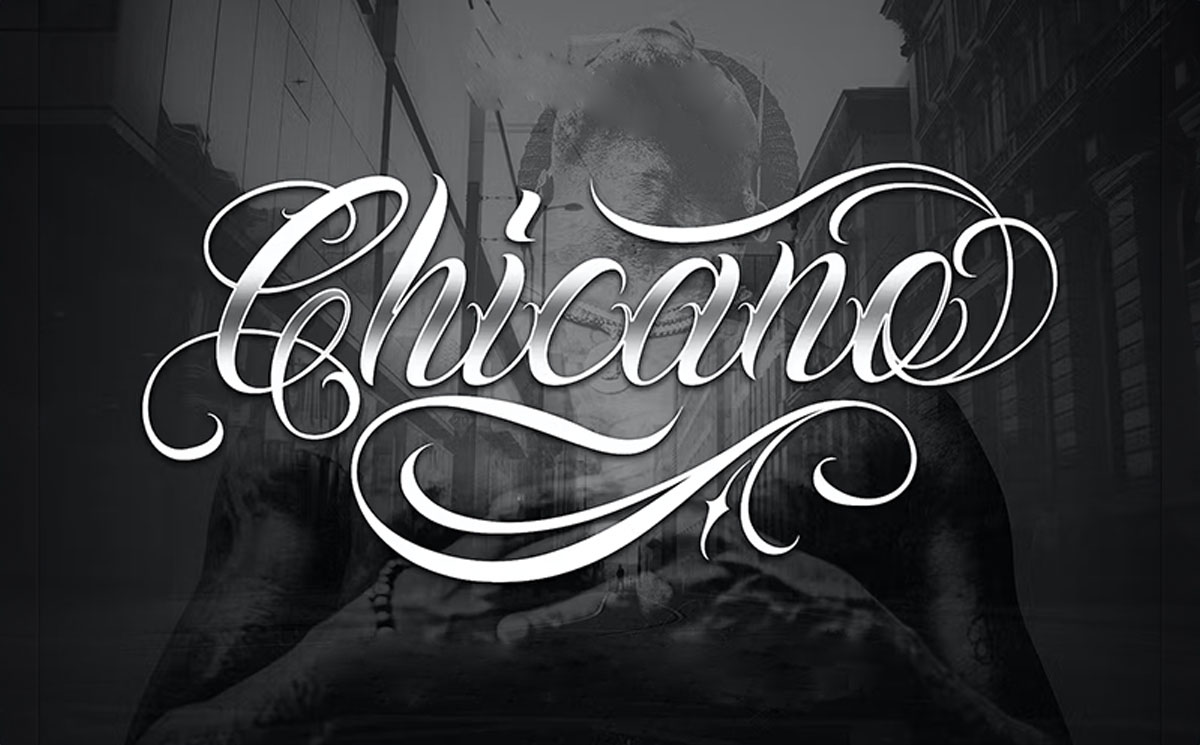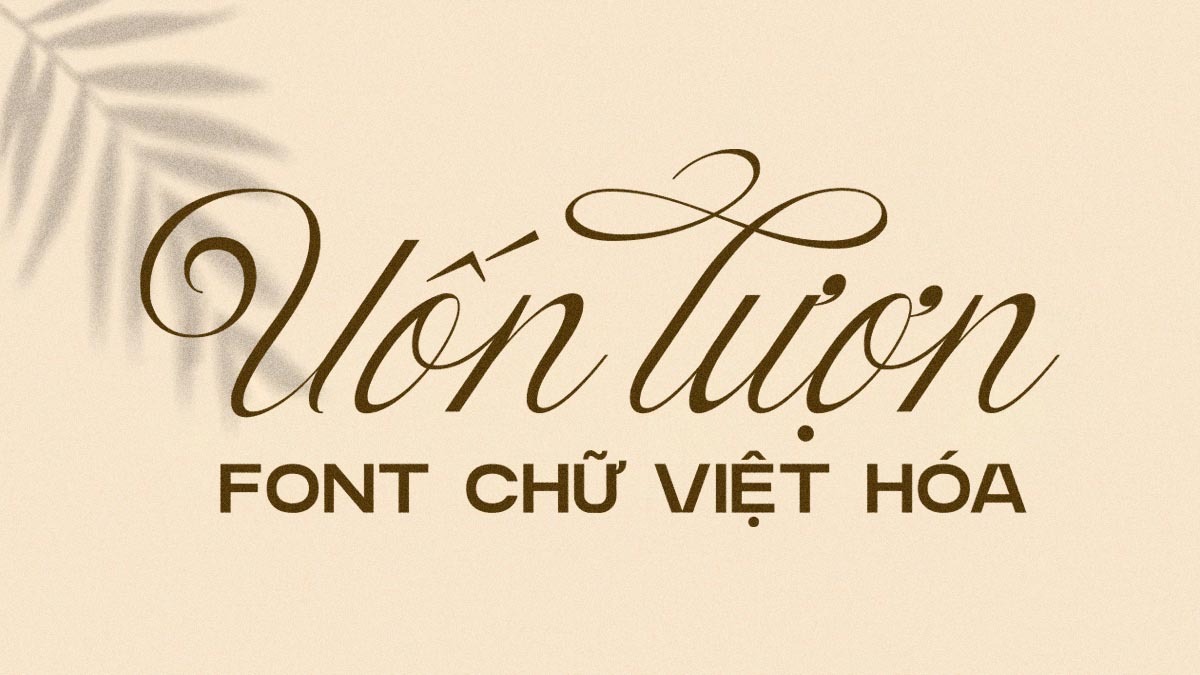
[Tải Xuống] TOP 10+ Font Chữ Uốn Lượn Mềm Mại Việt Hóa Đẹp Nhất 2025
Khám phá 10+ font uốn lượn Việt hóa mềm mại, nghệ thuật, lý tưởng cho thiệp, logo, typography. Hỗ trợ Canva, đầy đủ dấu tiếng Việt, dễ dùng.
Font chữ uốn lượn – Vẻ đẹp mềm mại trong từng nét viết
Trong thiết kế hiện đại, lựa chọn font chữ không đơn thuần là chọn kiểu dáng, mà còn là cách truyền tải cảm xúc và phong cách thị giác. Một trong những xu hướng đang được các nhà thiết kế ưa chuộng chính là font chữ uốn lượn – kiểu chữ có đường nét cong mềm, mang đậm cảm giác viết tay, đầy tính nghệ thuật và giàu cảm xúc.
Các font chữ uốn lượn Việt hóa ngày càng đa dạng, dễ sử dụng hơn bao giờ hết nhờ việc hỗ trợ đầy đủ dấu tiếng Việt, tương thích với các phần mềm thiết kế phổ biến như Canva, Photoshop, Illustrator… Dù bạn đang làm thiệp cưới, logo thương hiệu, typography nghệ thuật hay bài đăng mạng xã hội, font uốn lượn luôn là lựa chọn lý tưởng để tạo dấu ấn riêng.
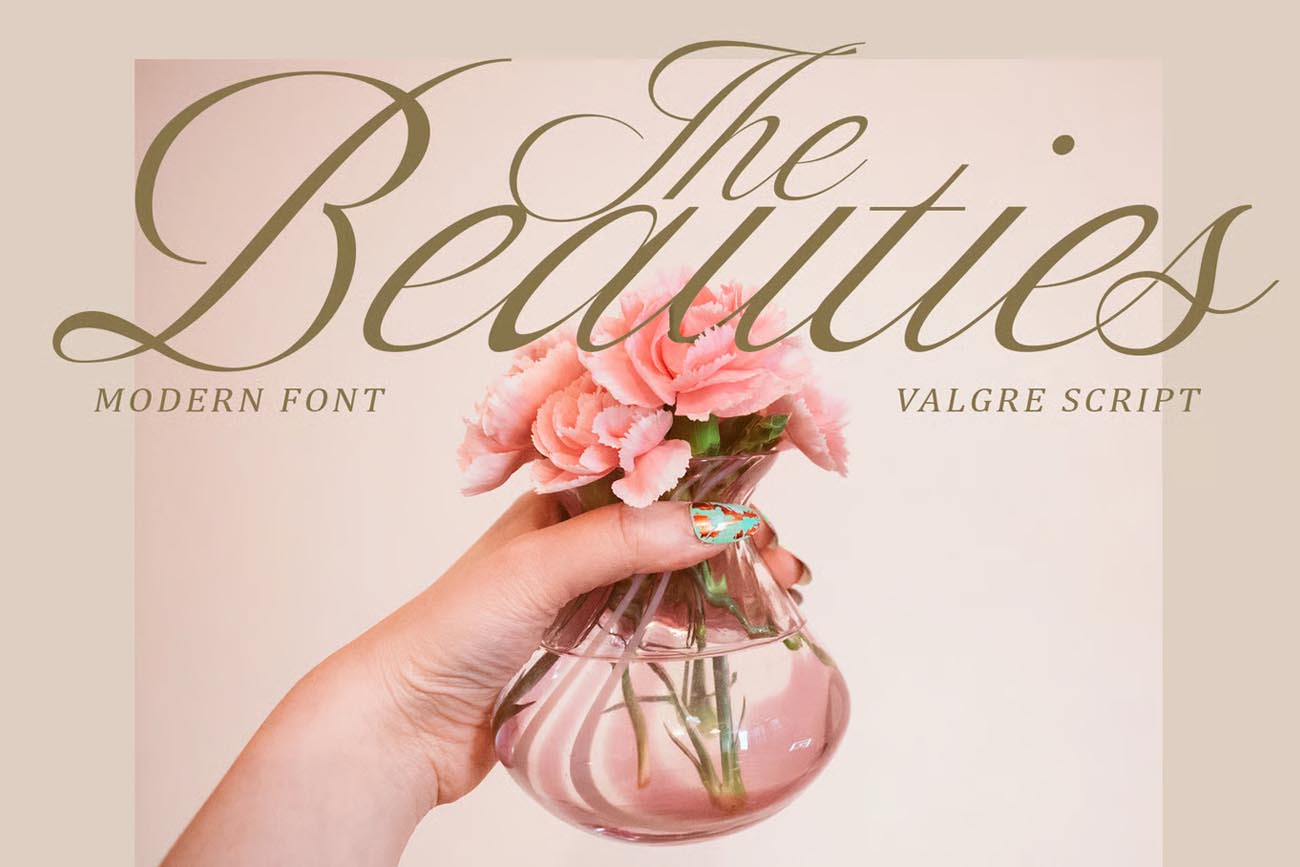
Kinh nghiệm chọn font chữ uốn lượn phù hợp
Trước khi tải về, hãy cân nhắc những yếu tố sau để chọn được bộ font uốn lượn dễ dùng và hiệu quả:
- Hỗ trợ đầy đủ tiếng Việt: Đảm bảo hiển thị đúng dấu và ký tự đặc biệt.
- Đường nét rõ ràng, dễ đọc: Dù uốn lượn nhưng không gây rối mắt.
- Có swash, alternate, glyphs phụ: Giúp bạn sáng tạo nhiều kiểu trình bày đẹp mắt.
- Dễ sử dụng trên Canva, PowerPoint, Illustrator, Photoshop.
- Phù hợp với phong cách thiết kế: Từ vintage, hiện đại đến phá cách cá tính.
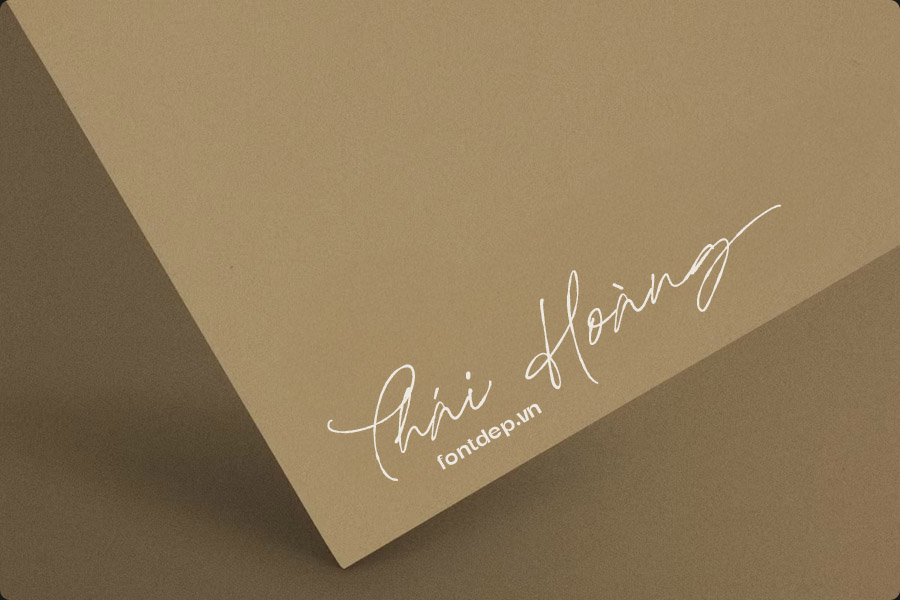
Top 10+ Font Chữ Uốn Lượn Việt Hóa Đẹp Nhất 2025
Dưới đây là những font chữ được Fontdep.vn tuyển chọn kỹ lưỡng – đảm bảo đẹp, dễ dùng và đã Việt hóa hoàn chỉnh:
TH Luxury 2 – Uốn Lượn & Thanh Lịch
TH Luxury 2 là một font chữ serif mang phong cách uốn lượn mềm mại, được thiết kế với độ tinh tế cao và tính nghệ thuật rõ nét. Các chữ cái có độ cao tương đối, nét mảnh và thanh thoát, trong khi những đường uốn cong tinh xảo ở các ký tự như “A”, “k”, “h” hay “n” tạo cảm giác chuyển động nhẹ nhàng. Đặc biệt, phần đuôi và đầu chữ được nhấn bằng các đường lượn duyên dáng, mang lại sự sang trọng và quý phái. TH Luxury 2 phù hợp cho các thiết kế cần sự nhẹ nhàng, nữ tính như thiệp cưới, bìa tạp chí cao cấp, hoặc logo mỹ phẩm.
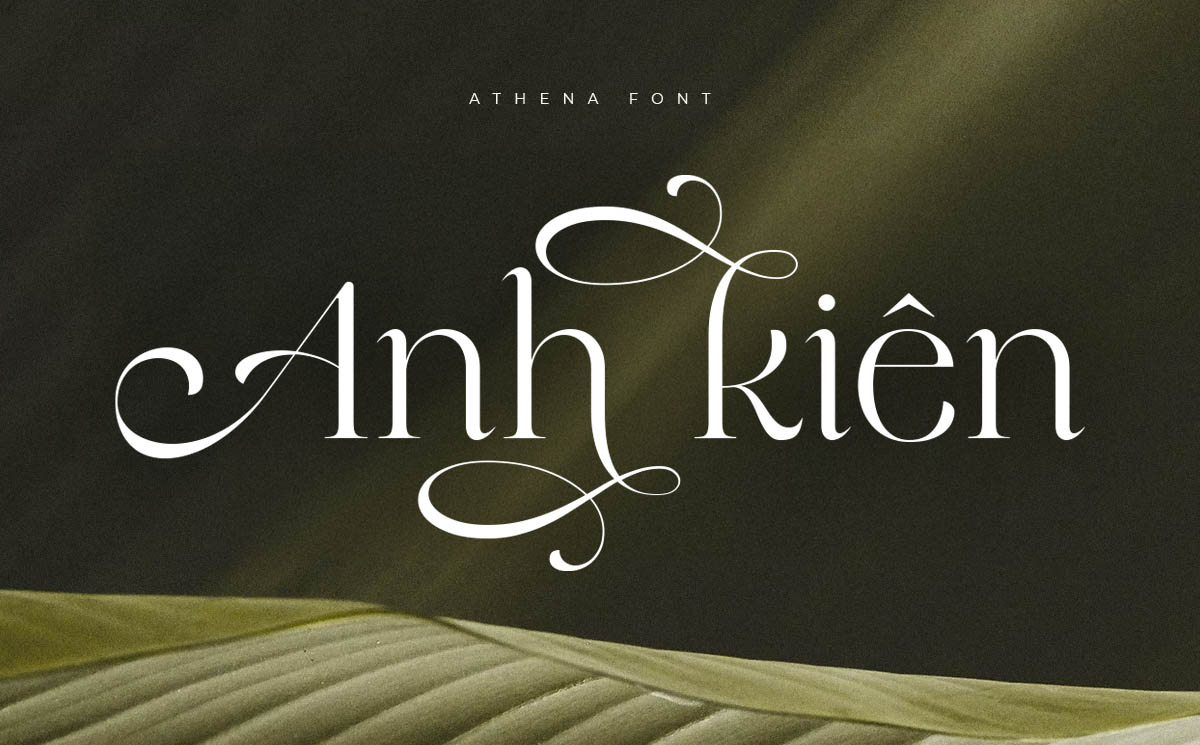
TH Pinland Regular – Mềm Mại & Hiện Đại
TH Pinland Regular là một kiểu font display có chân, nổi bật với những đường cong mềm mại và độ uốn lượn tinh tế. Phần đỉnh chữ và đuôi chữ được cách điệu dạng móc tròn, tạo nên vẻ duyên dáng đặc biệt cho các ký tự như “P”, “g” và “L”. Nét chữ dày vừa phải, các chi tiết trang trí swash ở chữ cái cuối giúp tổng thể trở nên mềm mại và bay bướm. Phong cách của font này gợi cảm giác trẻ trung, nữ tính, lý tưởng cho thiết kế logo thương hiệu mỹ phẩm, tiệm hoa, hoặc bìa tạp chí thời trang. TH Pinland mang lại ấn tượng tươi mới nhưng không kém phần sang trọng, rất phù hợp với xu hướng thiết kế hiện đại.
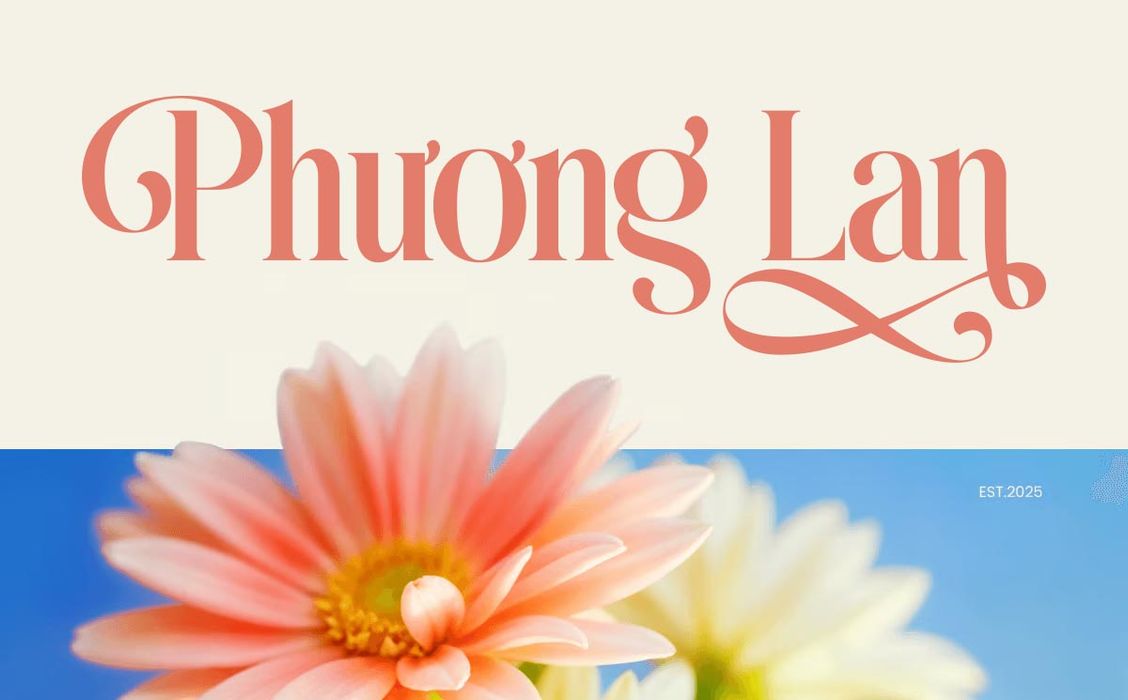
TH Viettay 4 – Viết Tay Bay Bướm
TH Viettay 4 là một kiểu chữ viết tay nghệ thuật mang dấu ấn hiện đại. Font nổi bật với những đường uốn cong lớn, mềm mại và kéo dài, tạo nên nhịp điệu thị giác uyển chuyển và lãng mạn. Nét chữ mảnh, thanh thoát nhưng vẫn giữ độ chắc chắn cần thiết để đảm bảo khả năng đọc tốt trong các thiết kế cảm xúc như poster nhạc trữ tình, lời bài hát, hay typography điện ảnh. Phong cách của TH Viettay 4 giúp khơi gợi hoài niệm và chiều sâu nội tâm – rất phù hợp cho các thiết kế mang tính kể chuyện hoặc truyền tải cảm xúc cá nhân.
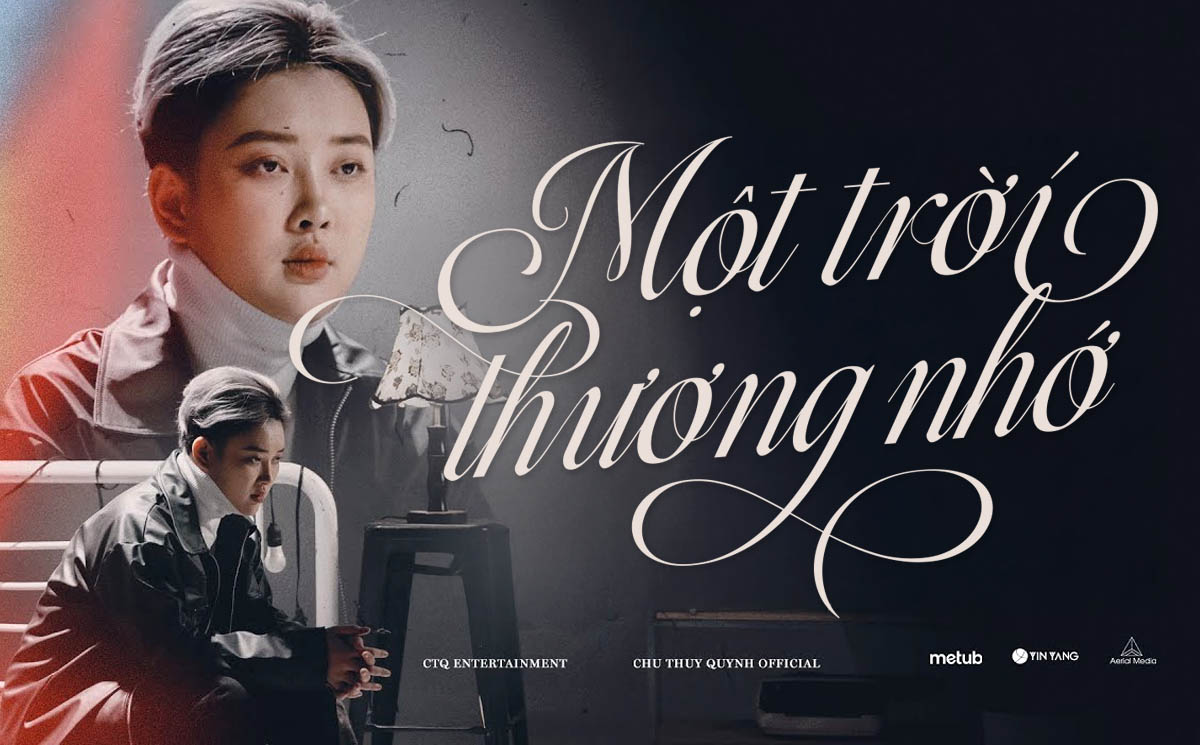
TH Viết Tay 2 – Mộng Mơ & Tinh Tế
TH Viết Tay 2 mang phong cách viết tay mềm mại, kết hợp hoàn hảo giữa nét bút tròn đều và những đường lượn tinh xảo. Các ký tự được liên kết mạch lạc, độ nghiêng nhẹ tạo cảm giác chuyển động tự nhiên, uyển chuyển. Điểm nhấn đặc biệt là phần swash mở rộng ở đầu và cuối chữ như “T”, “h”, “X”, tạo cảm giác bay bổng và đầy chất thơ. Font mang đến cảm giác trẻ trung, dịu dàng và gợi nhớ đến sự mộng mơ của tuổi thanh xuân. Đây là lựa chọn lý tưởng cho các thiết kế về chủ đề tình cảm, ảnh quote, thơ ca hoặc bìa sách mang sắc thái nhẹ nhàng, nữ tính.
- Việt hóa bởi: Phạm Sơn - Admin S99, Fontdep.vn
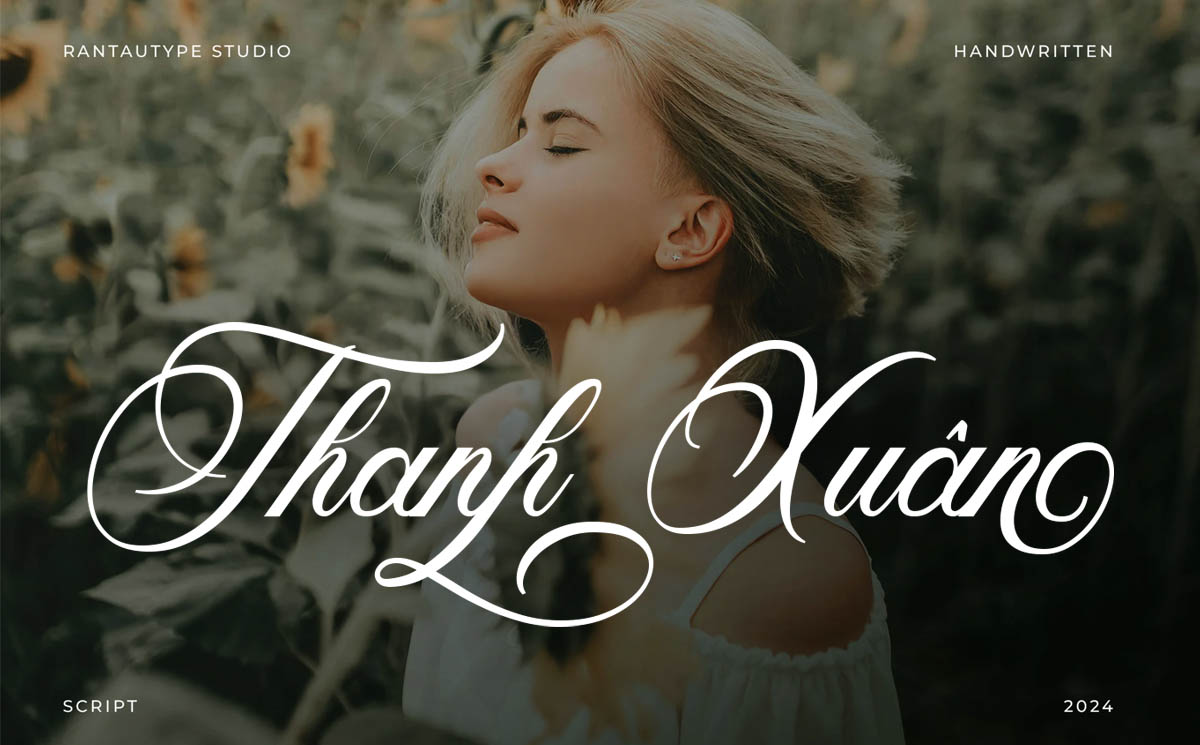
TH Viettay 5 – Thư Pháp & Hoài Cổ
TH Viettay 5 là một font chữ viết tay (handwriting script) có kiểu dáng thanh mảnh, độ nghiêng tự nhiên và những đường uốn lượn mềm mại. Nét chữ mảnh nhưng dứt khoát, kết hợp với các swash dài và tinh tế ở chữ cái đầu và cuối, tạo nên cảm giác chuyển động nhẹ nhàng và sang trọng. Font đặc biệt phù hợp với các thiết kế mang tính nghi lễ hoặc trang trọng như thiệp Tết, banner lời chúc, typography truyền thống. Sự bay bướm trong từng nét chữ giúp TH Viettay 5 truyền tải cảm xúc trang nhã, hoài cổ mà vẫn hiện đại – một lựa chọn lý tưởng cho các thiết kế cần yếu tố nghệ thuật và cảm xúc sâu lắng.
- Việt hóa bởi: Phạm Sơn - Admin S99, Fontdep.vn
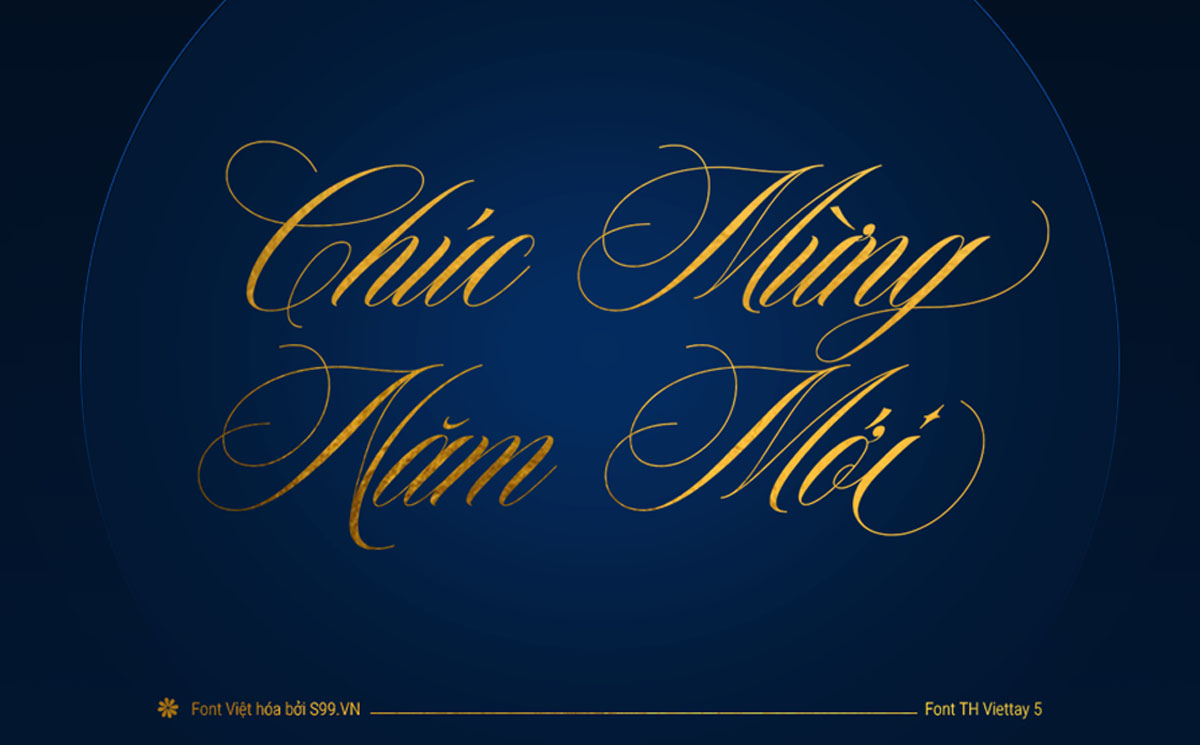
TH Honya – Cá Tính & Mềm Mại
TH Honya là font chữ viết tay (script) mang vẻ đẹp hiện đại, kết hợp hài hòa giữa nét thanh – đậm và các đường lượn duyên dáng. Điểm nổi bật của font nằm ở các nét móc và swash uốn lượn dài ở đầu và cuối chữ, đặc biệt là các ký tự như “S”, “g”, “y” được tạo hình cách điệu vô cùng bắt mắt. Kiểu dáng có độ nghiêng nhẹ, bố cục chữ rõ ràng, giúp TH Honya dễ đọc ngay cả khi được sử dụng trong thiết kế in ấn. Font phù hợp với các thiết kế mang hơi hướng lifestyle, làm đẹp, branding cá nhân hoặc social media, đem đến cảm giác mềm mại nhưng vẫn toát lên sự tự tin và độc đáo.
Kết Luận
Những font chữ uốn lượn Việt hóa không chỉ mang vẻ đẹp mềm mại mà còn truyền cảm xúc rất đặc biệt trong thiết kế. Dù bạn đang làm thiệp, logo, hay bài viết truyền cảm hứng – những bộ font trên chắc chắn sẽ giúp thiết kế của bạn trở nên ấn tượng và chuyên nghiệp hơn.